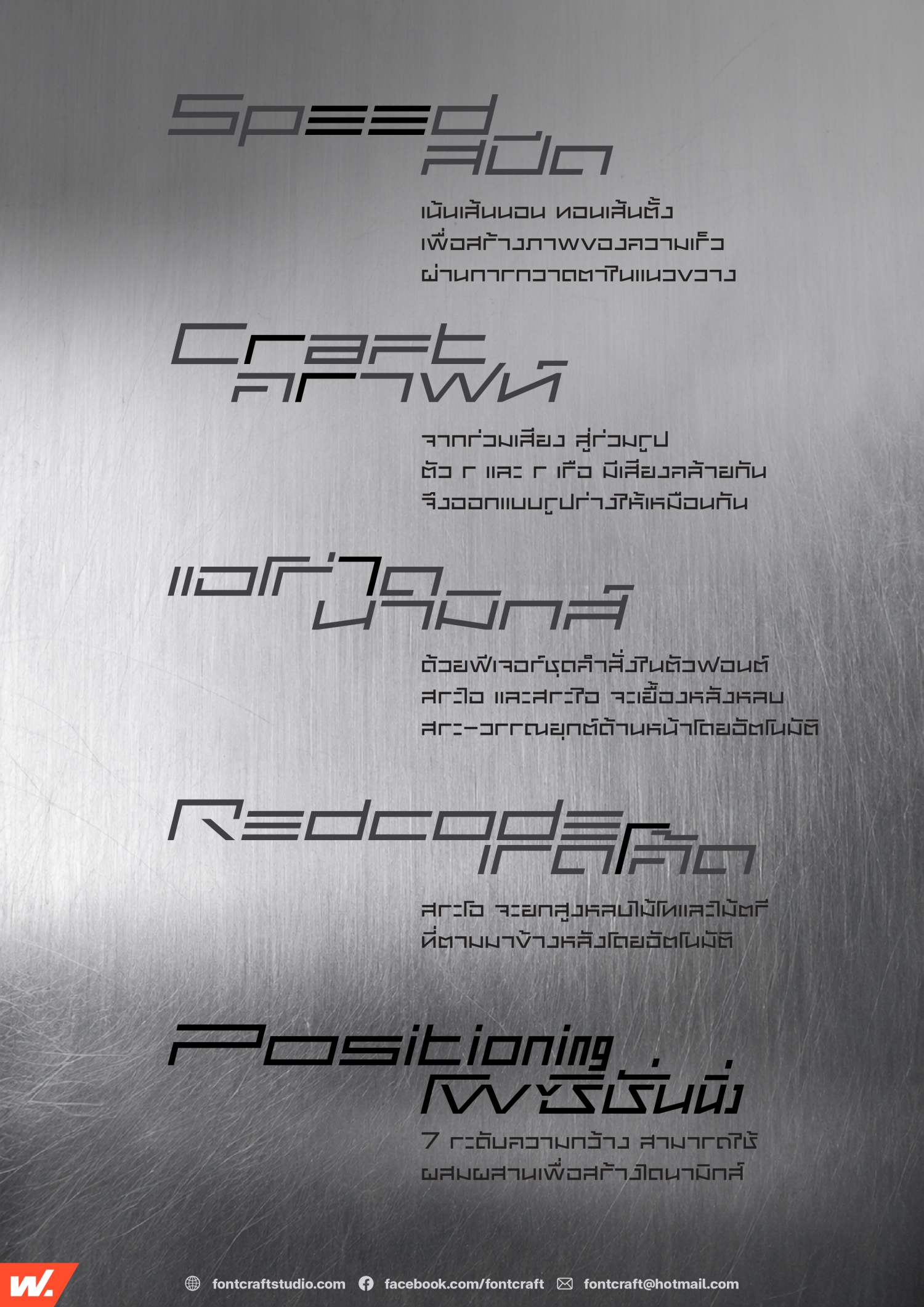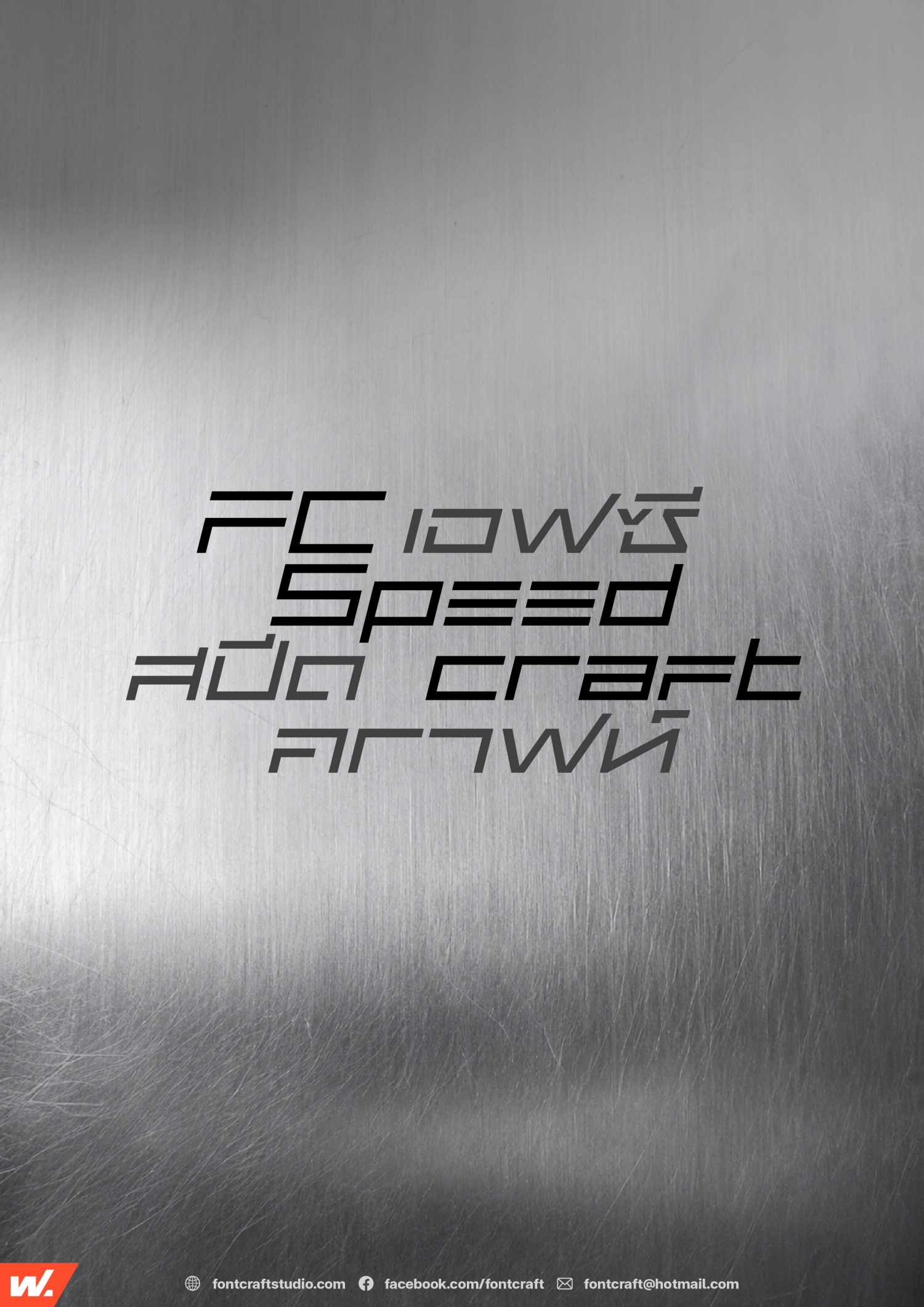
เอฟซี สปีดคราฟต์ (FC Speedcraft)
ฟอนต์เอฟซี สปีดคราฟต์ (FC Speedcraft)
จากรูปทรงสี่เหลี่ยม และแรงบันดาลใจจากยานยนต์ สู่แบบอักษรที่เป็นตัวแทนของความเร็ว แข็งแกร่ง พร้อมทะยานไปข้างหน้า
ลบโครงสร้างบางส่วน เน้นเส้นนอนทอนเส้นตั้ง เพื่อสร้างภาพของความเร็วผ่านการกวาดตาในแนวขวาง
จากร่วมเสียง สู่ร่วมรูป ตัว r และ ร เรือ มีเสียงคล้ายกัน จึงออกแบบรูปร่างให้เหมือนกัน
และด้วยฟีเจอร์ชุดคำสั่งในตัวฟอนต์สระไอ และสระใอ จะเยื้องหลังหลบสระ-วรรณยุกต์ด้านหน้าโดยอัตโนมัติ รวมถึงสระโอ จะยกสูงหลบไม้โทและไม้ตรีที่ตามมาข้างหลังโดยอัตโนมัติ
มาพร้อม 7 ระดับความกว้างและตัวเอนรวม 14 สไตล์ มี Variable Font แยกจากชุดปกติ